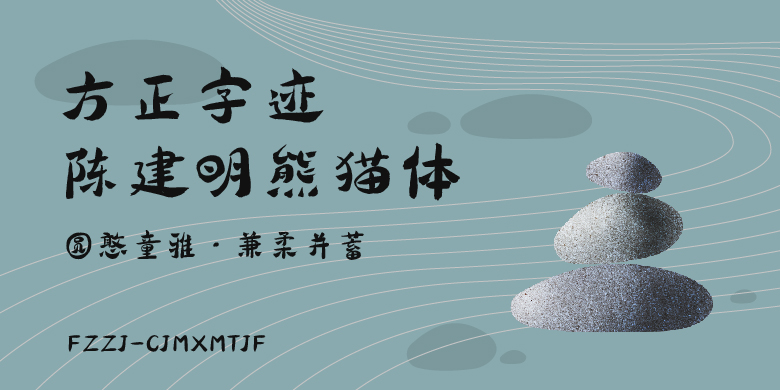
方正字迹-陈建明熊猫体
方正字迹-陈建明熊猫体是一款艺术字体,深受广大设计师的喜爱。
字体品牌: 方正字迹 设计师:陈建明 字体分类:创意书写 字体属性:精品字 字符集:大陆简体(GB2312-80)、简繁扩展(GBK) 发布时间: 2021
该字体以国宝熊猫的体态神韵、稀世珍存而设计的此款“熊猫字体”
,既承接了“童体字”随趣自在、圆憨童雅的艺术效果,又浸润了设计师集悟隶、颜字体之刚劲、憨厚、壮实之大成;扬弃并海纳宋体的规范布局,简洁明快,自然协调,融童体字之圆润而兼具动漫之灵动,可谓是字字珠玑,真活似“汉字熊猫”悠悠然自居与天地间的漫趣生活……“熊猫字体”既纳古法而蕴天地循环之大道于其中,又博采今日时代之弄潮时尚燃点于其外,兼柔并蓄,走转腾挪于方寸间,暗合道法自然之无为之道(无谓、无畏、无为)的传统文化的拙璞场景,也适用于动物世界、儿童青年读物、动感漫画、版画插图、电视电影制作等诸多现代文娱视界。